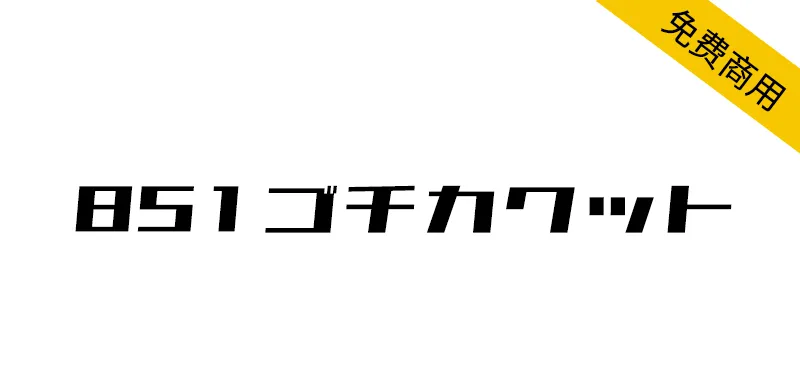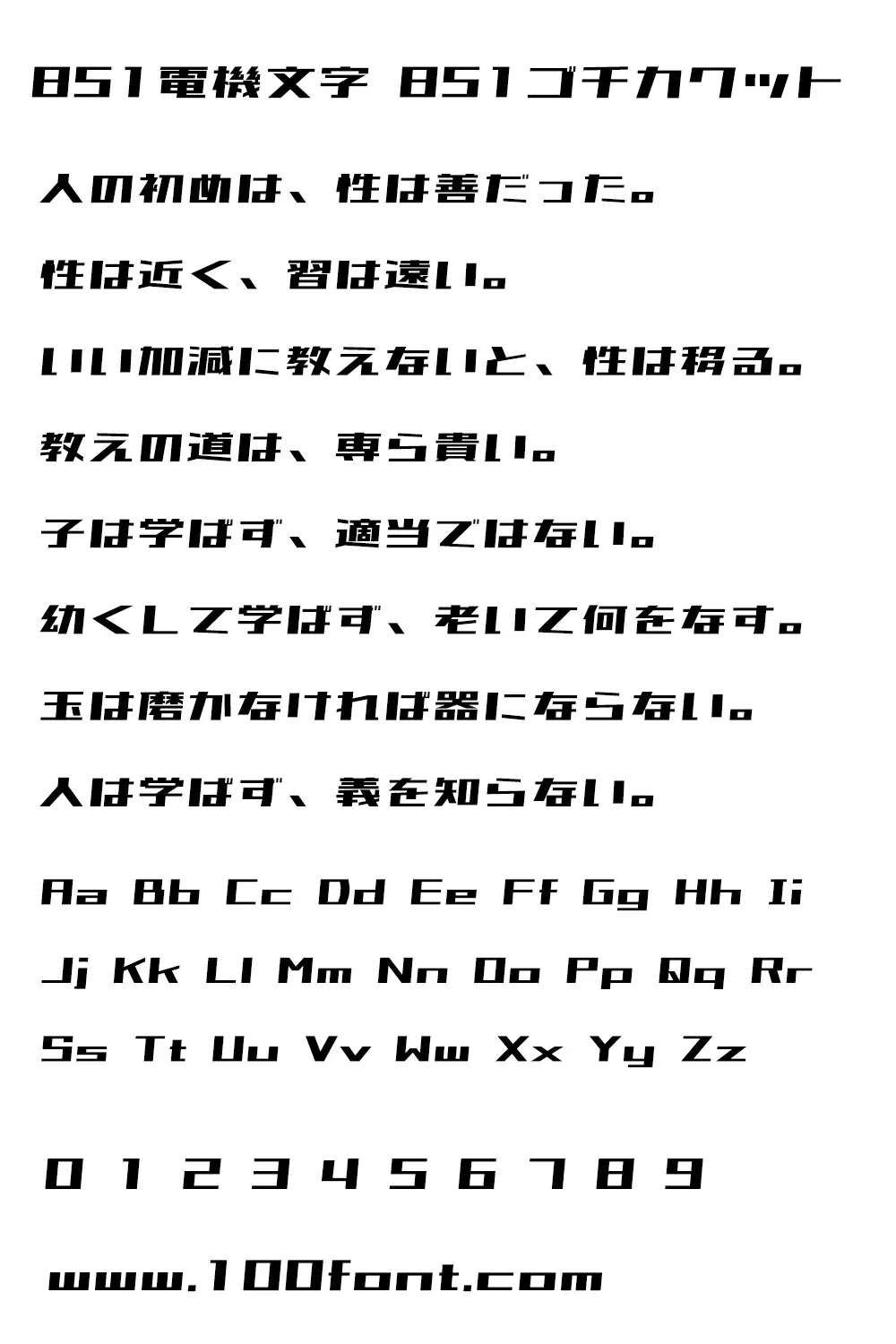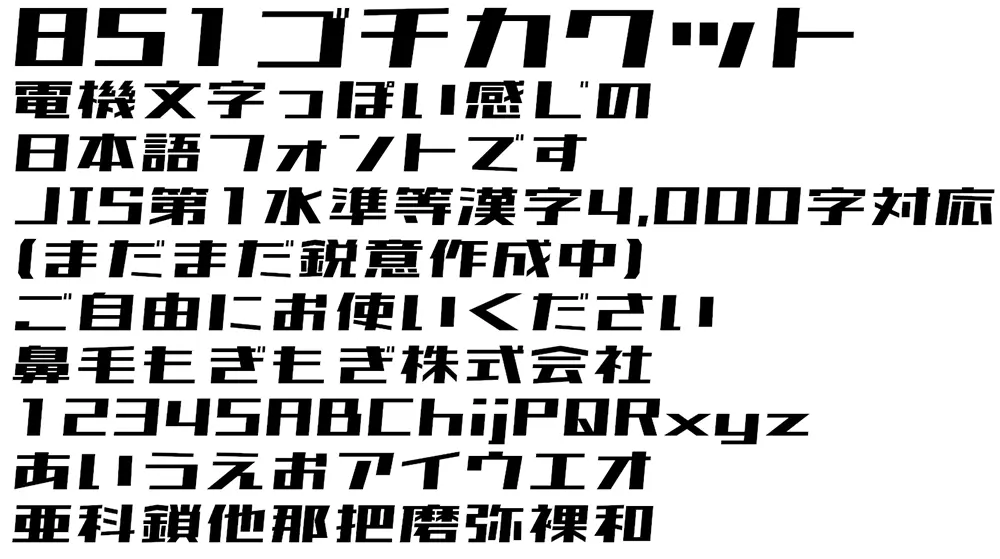
851電機文字體 851ゴチカクット預覽
851電機文字體 851ゴチカクット介紹
851電機文字體(851ゴチカクット)是由日本設計師 8:51:22 pm設計的一款充滿銳利感的剛性日本字體,筆畫和眾多現代美術體相似,延續了橫細豎粗的風格,豎畫傾斜5°,看上去很有速度感,適合應用於海報、banner 的標題處,當前字符數:5146個字符(不包括空格)。
對應文字:平假名、片假名、拉丁文字(英語)、數字、希臘文字、基里爾文字、記號(某種程度)、漢字(包括常用漢字/人名用漢字在內的4437個文字)、其他情況下追加的文字
注意:這款字體適用於繁體和日文,不適用於簡體中文,容易缺字。